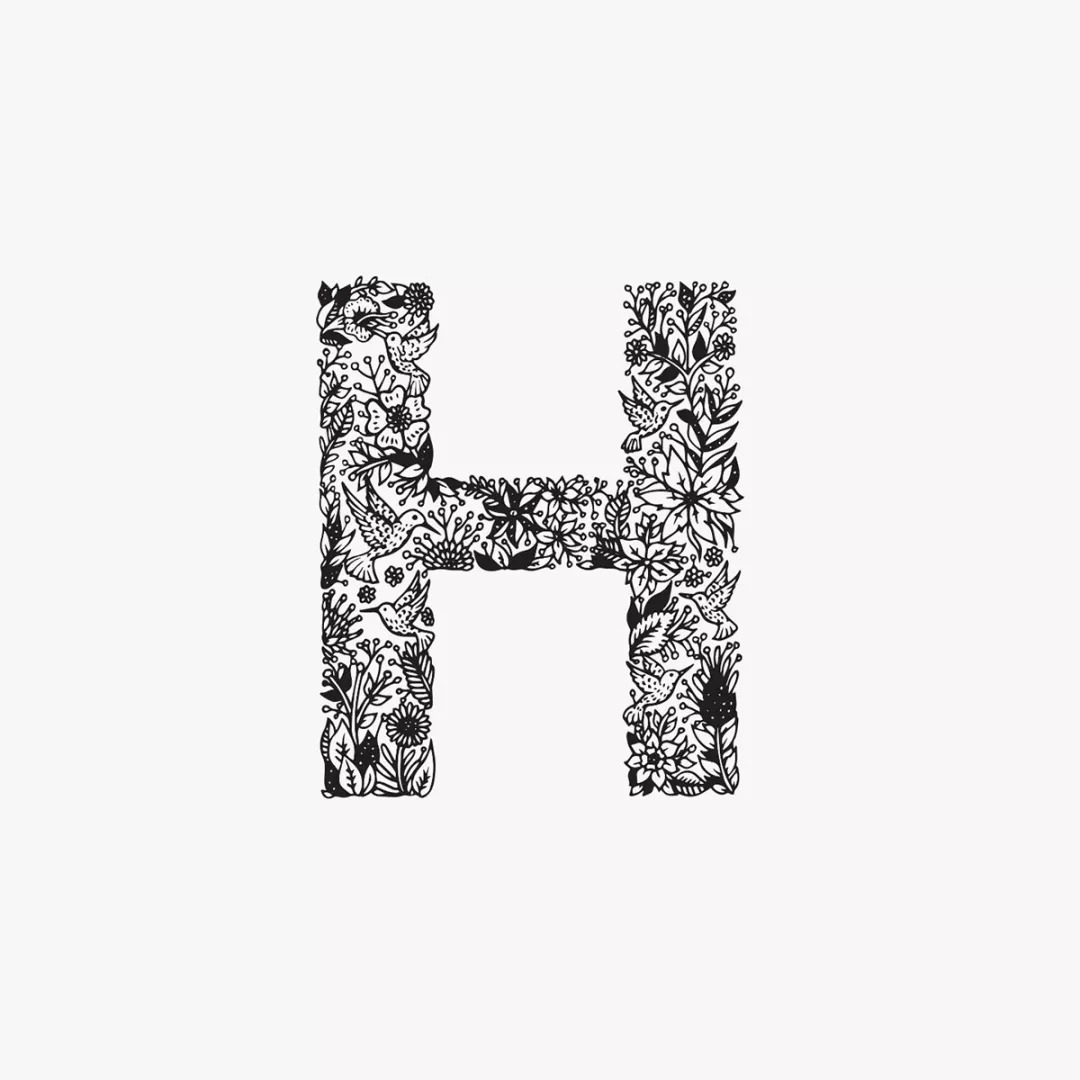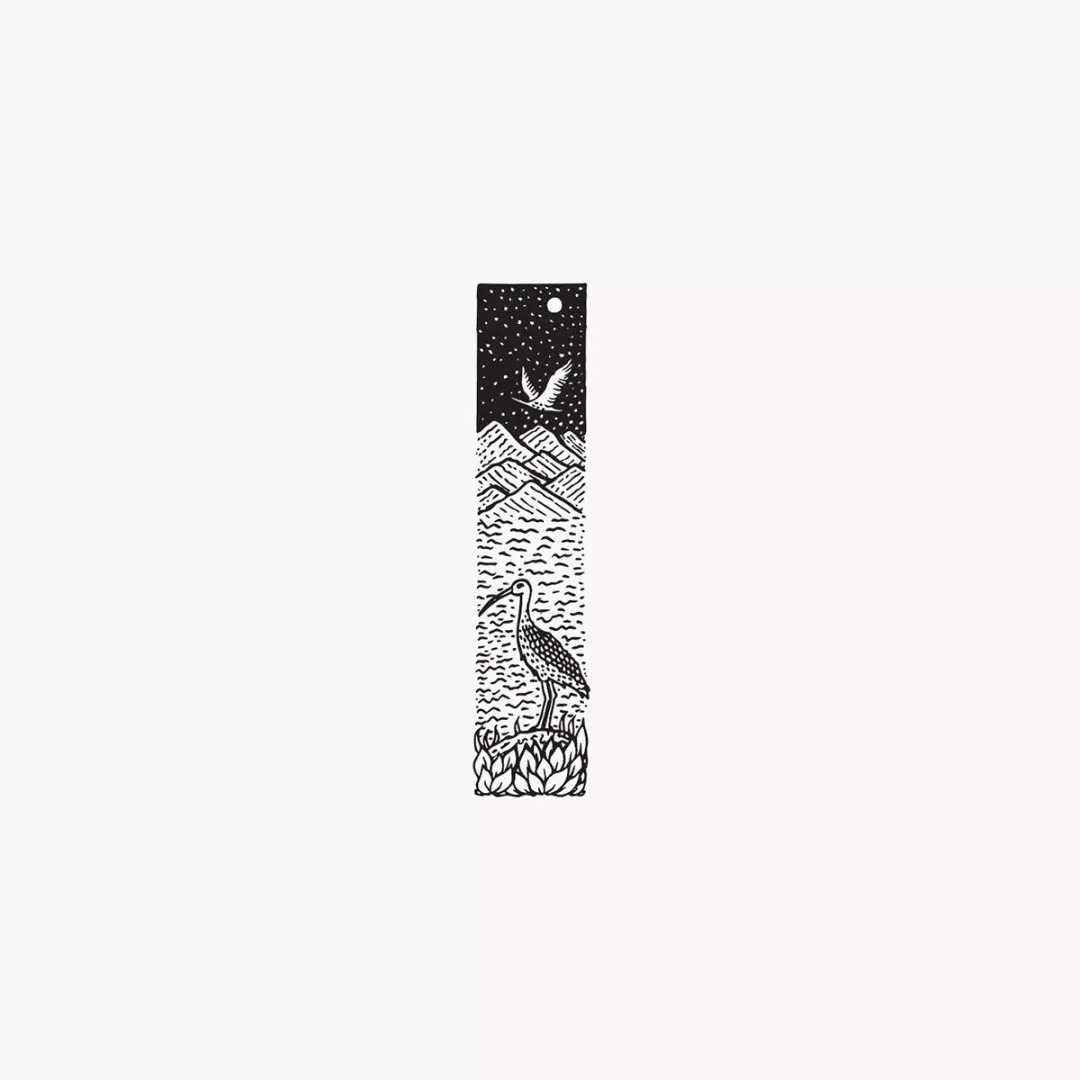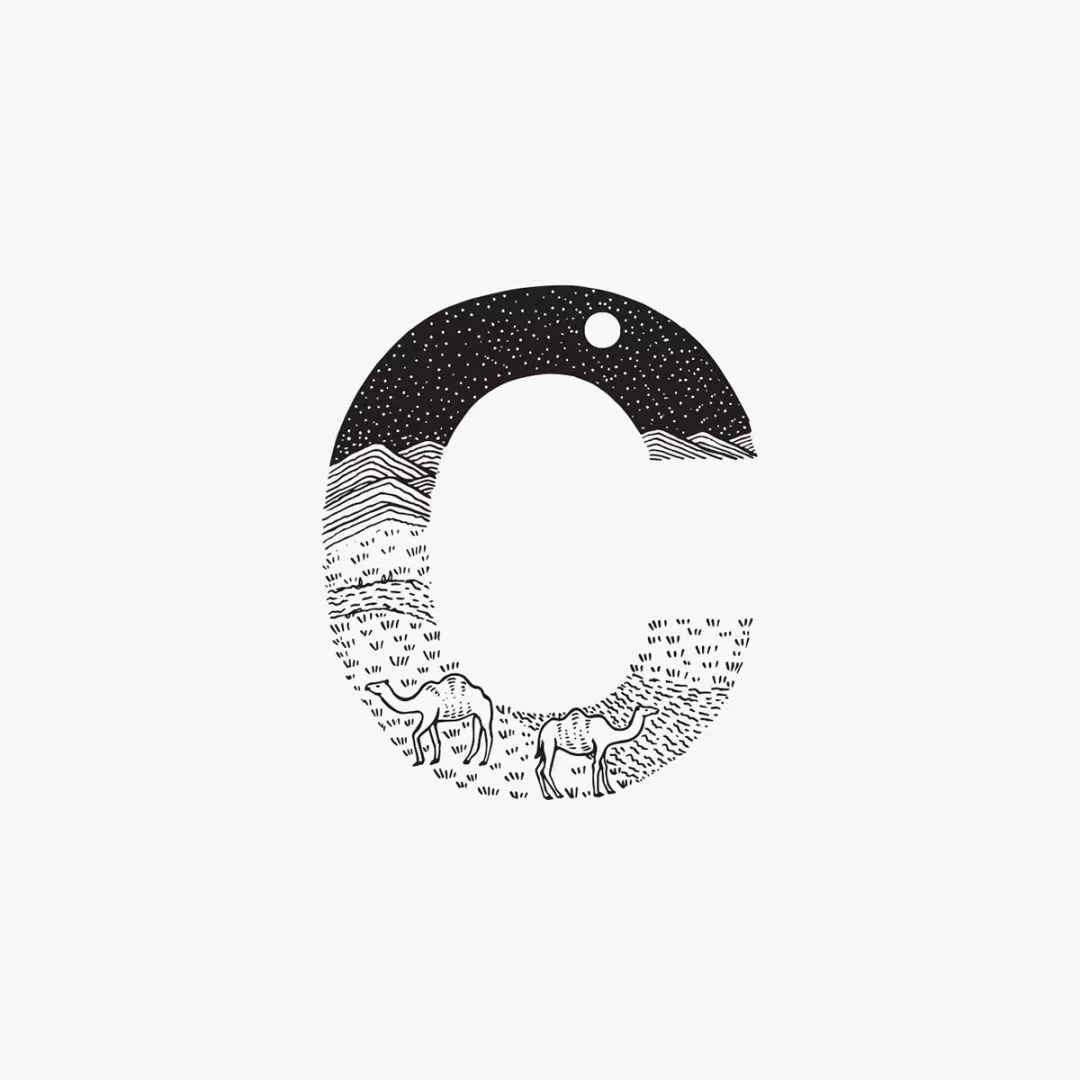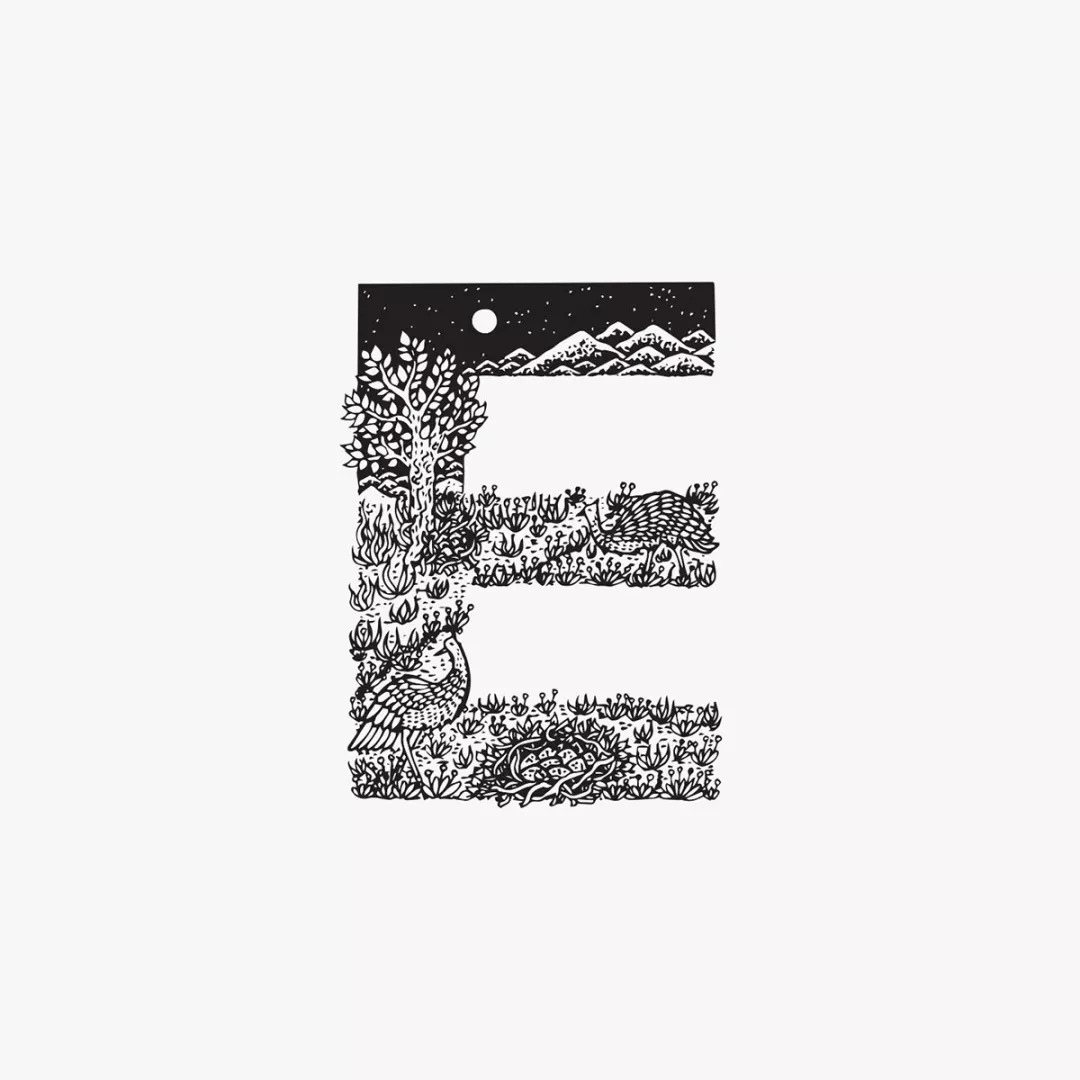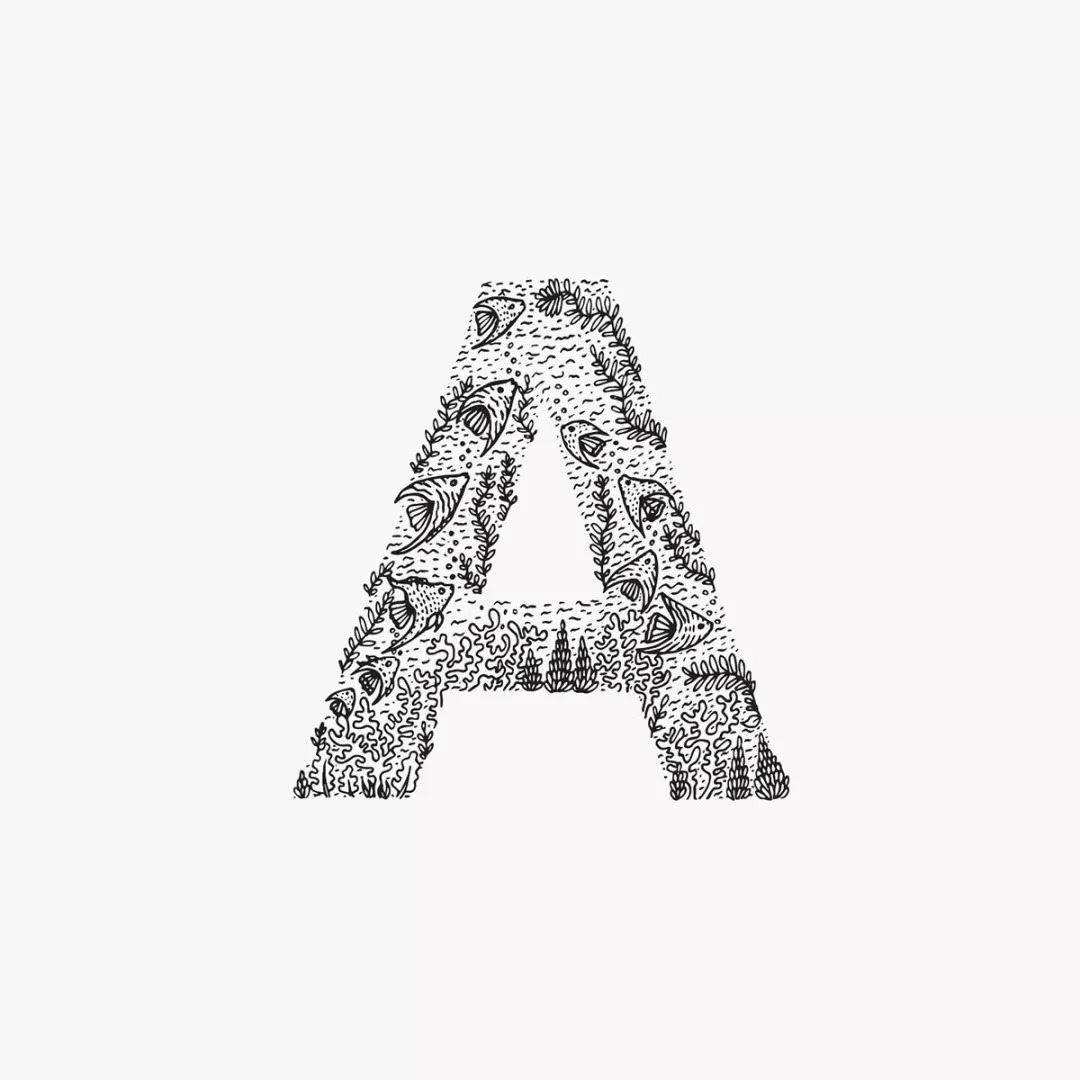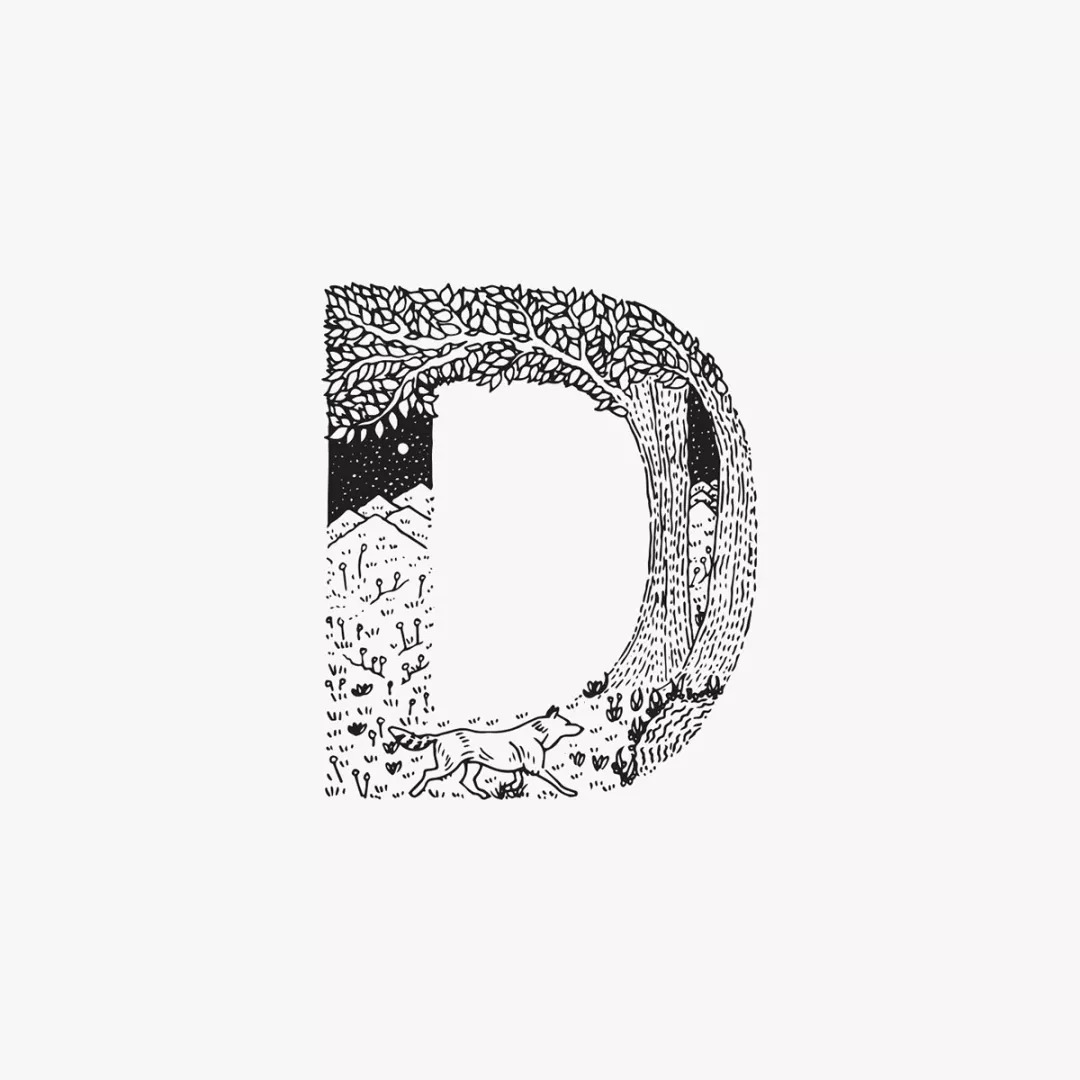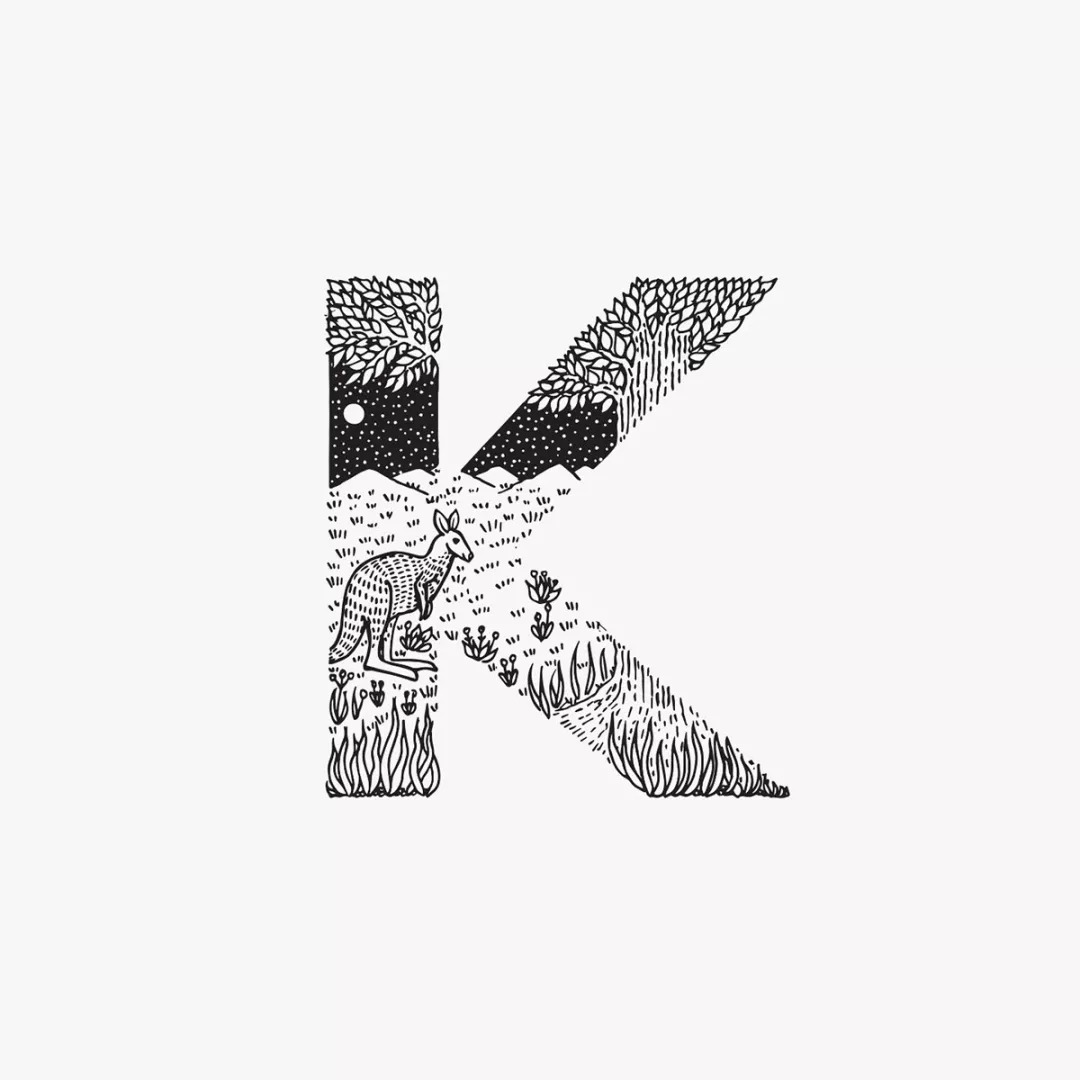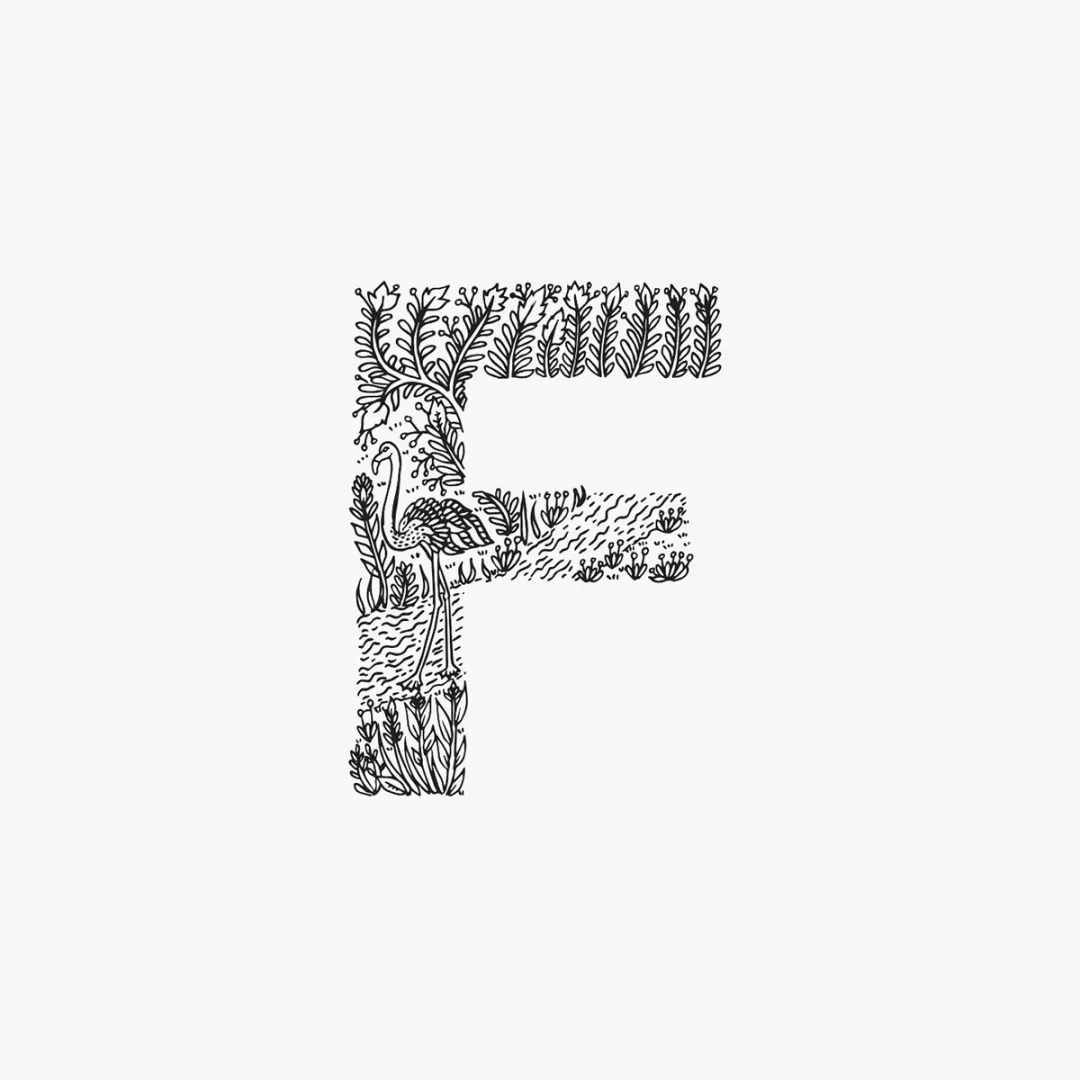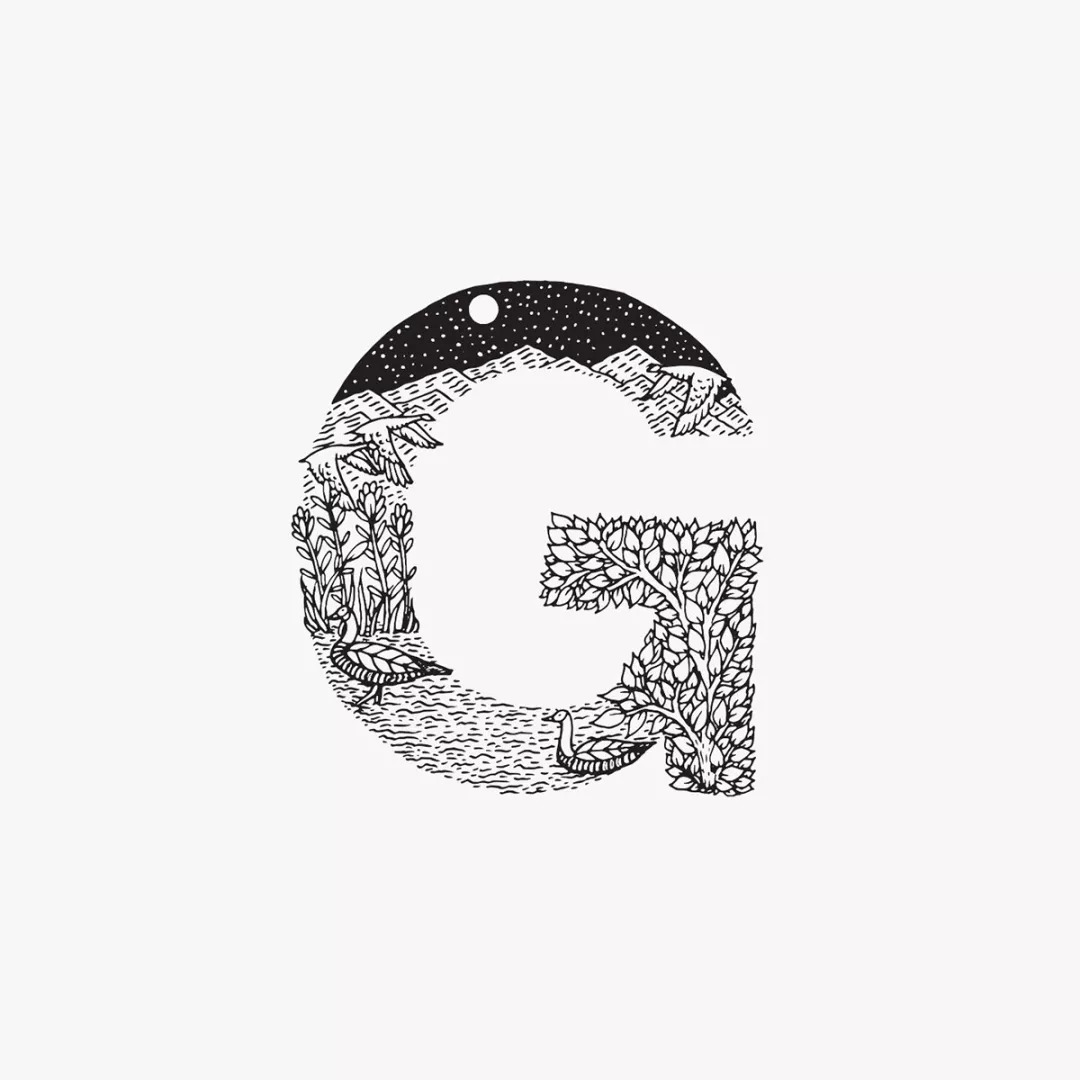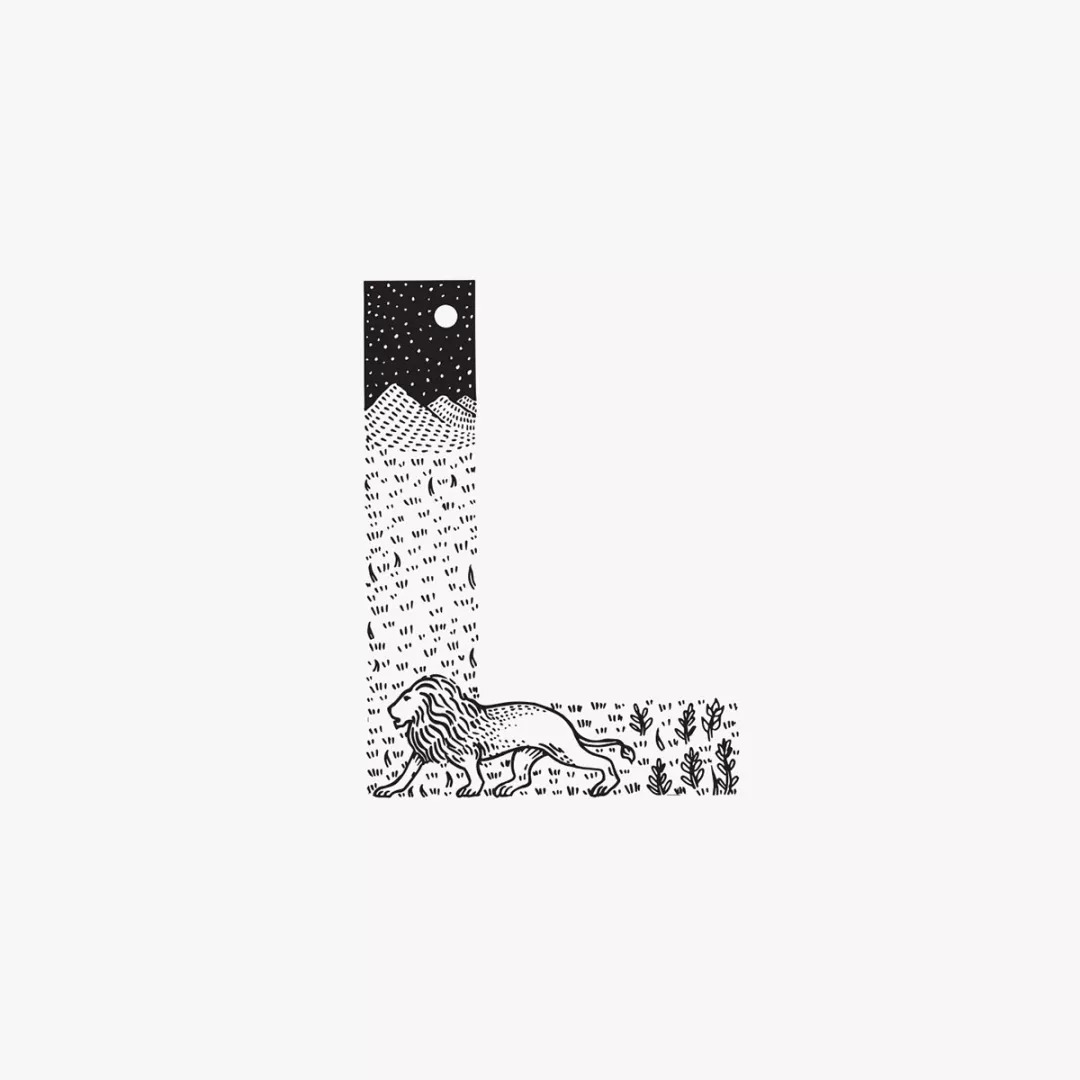
字母形状只是一块画布,活版动物字母设计案例
不知从什么时候起,婚礼上流行用新郎新娘的姓氏的大写首字母拼成花环,什么HM(黄和马)、CK(陈和孔)、LG(李和高)……偶尔碰上两人同姓的还要来个平方Y²。
现在有位来自希腊的插画师和平面设计师Meni Chatzipanagiotou,专门在26个英文字母上下功夫。与笔品牌Typman Ink合作,设计了一系列活版动物字母。
每一个字母都描绘了一种动物以及它的栖息地,黑白插画细腻整洁,令人惊叹的是,画面唤起了一种奇特的宁静之感,挂在卧室里当做装饰画最合适不过。
''A'' is for Angelfish
''B is for Beaver
''C'' is for Camel
''D'' is for Dingo
''E'' is for Emu
''F'' is for Flamingo
''G'' is for Goose
''H'' is for Hummingbirds
''I'' is for Ibis
''J'' is for Junco
''K'' is for Kangaroo
''L'' is for Lion
''M'' is for Moth
''N'' is for Nightingale
''O'' is for Owl
''P'' is for Peacock
''Q'' is for Quetzal
''R'' is for Rhinoceros
''S'' is for Stag
''T'' is for Turtle
''U'' is for Upupa
''V'' is for Viper
''W'' is for Whale
''X'' is for Xenops
''Y'' is for Yak
''Z'' is for Zebra
''&'' Ambersand